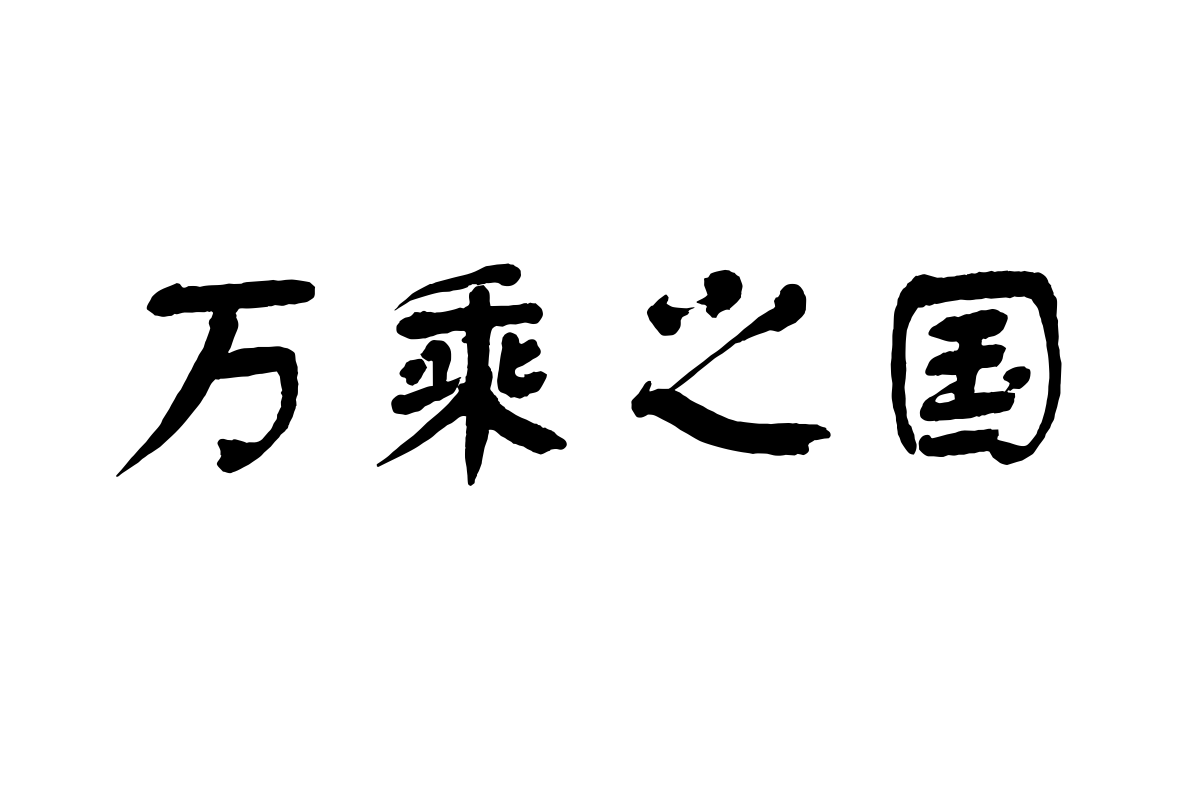
汉仪舒同体简字体是一套由汉仪公司设计并发布的中文字体,旨在为用户提供一种简洁、易读的字体选择。该字体的特点包括:
1. 字形清晰:汉仪舒同体简字体采用现代设计理念,字形结构紧凑,笔画流畅,易于阅读和识别。
2. 风格独特:汉仪舒同体简字体具有独特的设计风格,线条粗细适中,整体呈现出一种简约而不失美感的效果。